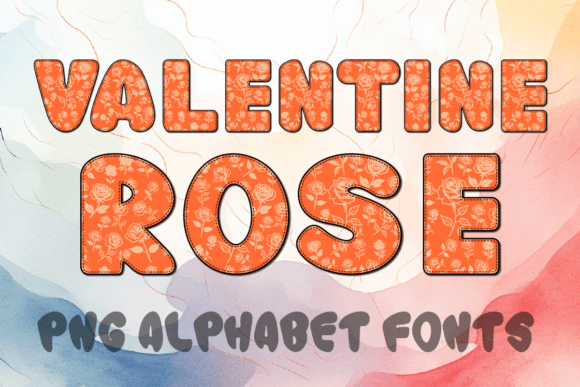
Valentine Rose Alphabet Fonts
หากคุณกำลังมองหาเนื้อหาคุณภาพสูงเช่น Valentine Rose Alphabet Fonts แพ็คเกจพรีเมียมนี้เป็นตัวเลือกที่ยอดเยี่ยมสำหรับโปรเจ็กต์สร้างสรรค์ของคุณ
ไม่ว่าคุณจะสร้างผลิตภัณฑ์ POD (Print on Demand) คำเชิญงานแต่งงาน หรือกราฟิกโซเชียลมีเดีย Valentine Rose Alphabet Fonts ก็เหมาะสมอย่างยิ่ง